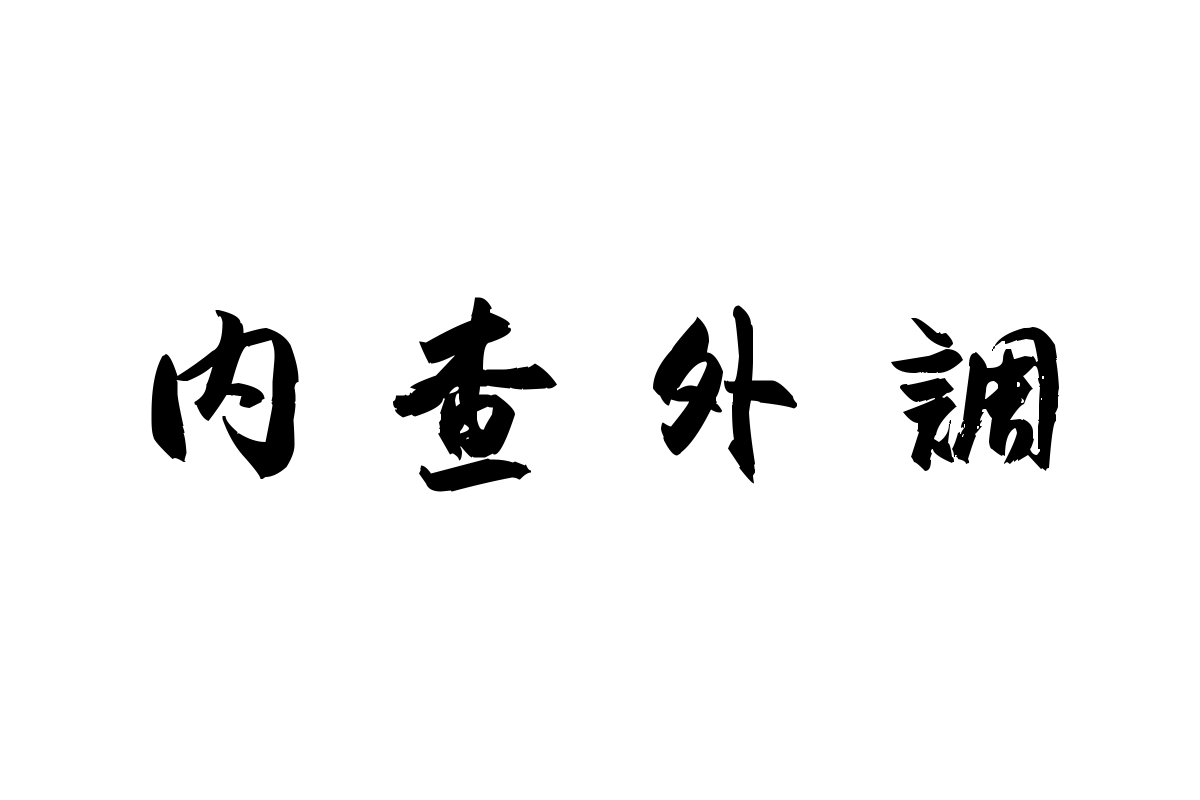
汉呈安景臣行书繁体字体是一种书法字体,属于行书范畴。它的特点是笔画流畅、结构紧凑,具有较强的艺术表现力和审美价值。该字体在设计时注重线条的粗细变化,使得整个字形显得更加生动有趣。同时,它还保留了一些传统的行书特点,如横竖撇捺等基本笔画的处理,使得字体既有现代感又不失传统韵味。总体来说,汉呈安景臣行书繁体字体是一款非常优秀的书法字体,适合用于各种需要展示书法艺术的场合。